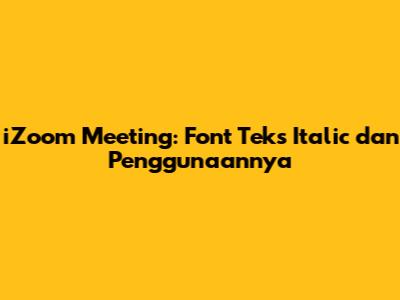
Hey guys! Pernah nggak sih kalian lagi asyik meeting online pakai iZoom, terus bingung sendiri pas lihat ada teks yang tampilannya miring alias italic? Nah, kali ini kita bakal kupas tuntas soal font italic di iZoom meeting. Apa sih sebenarnya fungsi teks italic itu, kenapa penting, dan bagaimana cara menggunakannya biar meeting kalian makin profesional dan informatif. iZoom, sebagai salah satu platform meeting online yang populer, terus berinovasi untuk memberikan pengalaman terbaik bagi penggunanya. Salah satu fitur kecil tapi penting yang seringkali terabaikan adalah kemampuan untuk memformat teks, termasuk menggunakan gaya italic. Tapi, banyak dari kita yang mungkin masih bertanya-tanya, kenapa sih ada teks miring? atau kapan sebaiknya saya pakai teks italic? Tenang, kalian datang ke tempat yang tepat. Kita akan bedah satu per satu, mulai dari definisi dasar sampai ke tips-tips praktis yang bisa langsung kalian terapkan. Jadi, siap-siap ya, karena setelah baca artikel ini, kalian bakal jadi pro dalam urusan formatting teks di iZoom meeting, bahkan mungkin di platform lain juga. Lupakan kebingungan soal teks italic, mari kita jelajahi dunia formatting yang seru ini bersama-sama! Memahami penggunaan teks italic yang tepat bisa jadi pembeda antara pesan yang sekadar tersampaikan dengan pesan yang benar-benar menonjol dan mudah dipahami. Ini bukan cuma soal estetika, lho, tapi lebih kepada kejelasan dan penekanan makna dalam komunikasi digital yang serba cepat ini. Yuk, kita mulai petualangan kita dalam memahami seluk-beluk italic di iZoom meeting.
Apa Itu Teks Italic dan Fungsinya?
Jadi gini, guys, teks italic itu apa sih? Sederhananya, italic adalah gaya penulisan di mana huruf-hurufnya terlihat sedikit miring ke kanan. Bayangin aja huruf biasa lagi santai, terus sedikit condong ke depan, gitu deh. Gaya ini biasanya digunakan untuk memberikan penekanan pada kata atau frasa tertentu dalam sebuah kalimat. Jadi, kalau kalian lihat ada kata yang dicetak miring, kemungkinan besar penulis ingin kalian memperhatikan kata itu secara khusus. Fungsinya banyak banget lho. Pertama, memberi penekanan. Ini fungsi utamanya. Misal, dalam percakapan iZoom, kamu mau menekankan satu poin penting, kamu bisa pakai italic. Contohnya, "Tolong selesaikan laporan ini sebelum jam 5 sore," nah, kata "Tolong" yang dicetak miring itu langsung menarik perhatian kan? Ini bikin audiens langsung tahu mana bagian yang paling krusial. Kedua, menunjukkan judul karya. Seperti judul buku, film, lagu, atau artikel. Jadi, kalau kalian lagi diskusi tentang sebuah karya, mencantumkan judulnya dalam format italic bakal bikin lebih rapi dan profesional. Misalnya, "Kita perlu mereferensikan artikel berjudul 'Strategi Pemasaran Digital Terbaru' untuk proyek kita." Ketiga, membedakan istilah asing atau kutipan. Kalau ada kata dari bahasa lain yang dipakai dalam bahasa Indonesia, atau kalau kalian mengutip langsung perkataan seseorang, italic bisa dipakai. Contohnya, kita sering dengar istilah "meeting point" dalam bahasa Inggris. Terus, kalau mengutip, bisa jadi seperti ini, "Seperti kata pepatah, 'Kesabaran adalah kunci.'" Keempat, menyoroti gagasan atau konsep baru. Kadang, dalam diskusi ilmiah atau teknis, ada istilah atau konsep yang baru diperkenalkan. Menggunakan italic bisa membantu membedakan ini dari teks biasa. Jadi, intinya, italic itu bukan sekadar gaya biar tulisan kelihatan keren, tapi punya peran penting dalam memperjelas makna, memberikan penekanan, dan meningkatkan keterbacaan. Di platform seperti iZoom meeting, di mana komunikasi seringkali cepat dan padat informasi, kemampuan menggunakan italic dengan tepat bisa jadi senjata ampuh buat bikin pesan kalian nggak cuma sampai, tapi juga dipahami dengan baik dan benar. Dengan memahami fungsi-fungsi ini, kalian bisa lebih percaya diri menggunakan italic untuk membuat komunikasi di iZoom meeting kalian jadi lebih efektif dan profesional, guys. Ini adalah elemen formatting dasar tapi sangat powerful.
iZoom Meeting dan Penggunaan Teks Italic
Nah, sekarang kita bahas gimana sih iZoom meeting itu sendiri terkait teks italic. Sejujurnya, kebanyakan platform meeting online, termasuk iZoom, biasanya nggak punya fitur dedicated untuk memformat teks secara real-time saat kalian lagi presentasi atau chat di dalam meeting itu sendiri, kecuali kalau kalian lagi pakai fitur whiteboard atau semacamnya yang memang mendukung editor teks. Tapi, jangan salah paham dulu, guys! Ini bukan berarti italic nggak relevan di iZoom meeting, lho. Justru sebaliknya, memahami dan menggunakan italic dengan bijak itu sangat penting, terutama kalau kalian menyiapkan materi presentasi atau catatan sebelum meeting dimulai. Misalnya, kalian lagi nyiapin slide presentasi pakai PowerPoint atau Google Slides, nah di situ kalian pasti punya opsi untuk bikin teks jadi italic. Ketika materi itu nanti kalian tampilkan di iZoom meeting, audiens akan melihat teks italic yang sudah kalian siapkan. Ini tujuannya agar informasi yang kalian sampaikan jadi lebih terstruktur dan mudah ditangkap. Penekanan pada poin penting akan terlihat jelas di slide, yang kemudian akan kalian jelaskan lebih lanjut secara lisan. Begitu juga kalau kalian bikin catatan untuk diri sendiri atau briefing untuk tim sebelum meeting iZoom dimulai. Menggunakan italic di dokumen catatan itu akan membantu kalian fokus pada poin-poin kunci saat sesi diskusi nanti. Jadi, meskipun iZoom meeting-nya sendiri mungkin nggak punya tombol 'Italic' yang bisa diklik langsung saat obrolan berlangsung, konsep dan penggunaan italic tetap krusial dalam persiapan dan penyampaian informasi. Pikirkan saja seperti ini: italic itu adalah alat bantu visual untuk menyampaikan nada atau makna tertentu dalam tulisan. Saat kalian membuat dokumen, e-mail, atau materi presentasi yang akan dibagikan atau dibahas di iZoom meeting, penggunaan italic ini membantu memecah kebosanan visual dan mengarahkan perhatian pembaca atau pendengar ke elemen-elemen yang paling penting. Contoh konkretnya, kalau kalian lagi bikin agenda meeting iZoom, kalian bisa bikin judul sesi pakai italic, atau kalau ada kata kunci penting yang perlu diingat, italicin aja! Ini membantu semua orang yang terlibat dalam meeting jadi lebih fokus dan nggak kehilangan track dari topik yang dibahas. Jadi, meskipun fitur built-in-nya mungkin terbatas saat meeting berlangsung, persiapan materi dengan format italic adalah kunci agar komunikasi di iZoom meeting jadi lebih efektif dan profesional. Ini tentang bagaimana kita menggunakan alat yang ada, bahkan di luar platform meeting itu sendiri, untuk menunjang kelancaran komunikasi kita di dalam platform tersebut. iZoom meeting kan cuma wadahnya, tapi konten dan cara penyampaiannya tetap ada di tangan kita, guys!
Kapan Sebaiknya Menggunakan Teks Italic di iZoom Meeting?
Oke, guys, sekarang kita masuk ke bagian yang paling seru: kapan sih momen yang tepat buat pakai teks italic pas lagi ngomongin atau nyiapin sesuatu buat iZoom meeting? Ini penting biar nggak salah kaprah dan malah bikin bingung. Ingat, italic itu bukan buat gaya-gayaan doang, tapi punya tujuan. Fungsi utama italic adalah penekanan, jadi pakai aja pas kalian mau bikin satu kata atau frasa jadi super penting dan harus diperhatikan sama semua orang di meeting. Misalnya, waktu kalian lagi ngasih arahan penting ke tim. Coba deh, bayangin kalian lagi ngomong di iZoom, terus ada poin yang kritis banget. Kalian bisa bilang, "Ingat ya, deadline pengumpulan data itu besok pagi, bukan lusa!" Kata "Ingat" atau seluruh frasa "Ingat ya, deadline pengumpulan data itu besok pagi, bukan lusa!" yang dicetak miring di catatan atau slide kalian, itu langsung bikin pendengar lebih fokus dan nggak salah paham soal tenggat waktu. Fungsi kedua yang nggak kalah penting adalah untuk identitas karya. Jadi, kalau kalian lagi diskusi tentang buku, film, lagu, atau bahkan nama proyek, nah itu pas banget kalau ditulis pakai italic. Contohnya di iZoom, kalian bisa bilang, "Kita perlu baca buku 'Atomic Habits' untuk dapat inspirasi." Ini bikin judul buku jadi jelas dan terpisah dari kalimat biasa. Kelihatan lebih profesional, kan? Terus, ketika kalian perlu menyoroti istilah asing atau istilah teknis yang mungkin belum familiar buat semua orang. Misalnya, ada istilah baru dalam dunia marketing yang lagi dibahas, kayak 'influencer marketing' atau 'SEO audit'. Menuliskannya dalam italic bisa membantu audiens membedakan ini sebagai istilah khusus. Ini juga berlaku kalau kalian pakai kutipan langsung dari sumber lain. Anggap aja kayak kalian ngasih tahu, "Ini bukan kata-kata saya, tapi kata-kata dari sumber lain." Contohnya, "Seperti yang disampaikan oleh Pak Budi, 'inovasi adalah kunci pertumbuhan bisnis.'" Ini menjaga integritas dan kejelasan sumber informasi. Terakhir, tapi nggak kalah penting, gunakan italic untuk membedakan peran atau status. Misalnya, kalau dalam satu dokumen ada daftar tugas, kalian bisa menandai tugas yang sifatnya urgent dengan italic. Atau, kalau kalian lagi diskusi soal peran dalam proyek, kalian bisa tulis: 'Project Manager', 'Lead Developer', 'Marketing Specialist' dalam format italic untuk menunjukkan peran-peran tersebut. Yang terpenting, jangan berlebihan, guys! Pakai italic secukupnya saja. Kalau terlalu banyak teks yang dimiringkan, efek penekanannya malah hilang dan bikin mata lelah. Gunakan secara strategis untuk poin-poin yang benar-benar butuh perhatian ekstra. Dengan memahami kapan dan bagaimana menggunakan italic dengan tepat, komunikasi kalian di iZoom meeting, baik itu saat persiapan materi, saat presentasi, maupun saat berbagi catatan, akan jadi jauh lebih efektif, jelas, dan profesional. Jadi, jangan ragu untuk memanfaatkan kekuatan italic ini, tapi ingat, kuncinya adalah moderasi dan tujuan yang jelas.
Tips Menggunakan Teks Italic Agar Lebih Efektif di iZoom Meeting
Supaya penggunaan teks italic kalian di iZoom meeting jadi makin nampol dan nggak sia-sia, nih ada beberapa tips jitu buat kalian, guys. Pertama, selalu utamakan kejelasan, bukan sekadar gaya. Ingat, tujuan utama italic adalah untuk memberi penekanan atau membedakan sesuatu. Jadi, sebelum kalian miringin teks, tanya dulu ke diri sendiri: 'Apakah ini benar-benar perlu?' Kalau jawabannya 'iya', baru deh pakai. Jangan sampai gara-gara italic, malah bikin orang bingung baca atau malah kelihatan norak. Penekanan yang cerdas itu kuncinya. Kedua, gunakan secara konsisten. Kalau kalian sudah memutuskan untuk menggunakan italic untuk menandai judul buku, misalnya, maka lakukan itu terus-menerus di semua materi yang berhubungan dengan iZoom meeting kalian. Konsistensi ini membantu membangun kebiasaan baik dan membuat audiens lebih mudah mengenali pola informasi. Jadi, mereka nggak perlu mikir dua kali, "Ini judul buku atau bukan ya?" Ketiga, padukan dengan elemen formatting lain dengan bijak. Italic memang bagus, tapi jangan sampai sendirian. Kalian bisa kombinasikan dengan bold untuk penekanan yang lebih kuat, atau pakai bullet points untuk daftar. Tapi ingat, jangan terlalu ramai. Terlalu banyak gaya formatting dalam satu kalimat atau paragraf itu bikin pusing. Cukup gunakan kombinasi yang membuat informasi lebih mudah dicerna. Kombinasi italic dan bold itu seringkali jadi pilihan yang bagus untuk menyoroti poin yang sangat penting. Keempat, perhatikan audiens kalian. Kalau kalian meeting dengan tim internal yang sudah paham jargon kalian, mungkin penggunaan italic untuk istilah teknis bisa lebih bebas. Tapi kalau audiensnya campuran, atau ada orang baru, lebih baik gunakan italic untuk istilah asing atau teknis dengan penjelasan tambahan. Tujuannya agar semua orang bisa on the same page. Memahami siapa yang membaca atau mendengar itu penting banget. Kelima, latih penggunaan italic dalam materi persiapan. Karena fitur italic di iZoom meeting saat sesi berlangsung mungkin terbatas, fokuslah pada bagaimana kalian bisa memaksimalkan penggunaannya di slide presentasi, dokumen, atau catatan yang akan kalian bagikan. Latih diri kalian untuk mengidentifikasi kapan sebuah kata atau frasa pantas untuk diberi penekanan italic. Keenam, hindari penggunaan italic untuk teks yang panjang. Italic itu efektif untuk kata atau frasa pendek. Kalau kalian miringin satu paragraf penuh, itu bakal susah dibaca dan bikin mata cepat lelah. Fokus pada detail, bukan keseluruhan. Terakhir, selalu review dan minta feedback. Setelah kalian menyiapkan materi dengan penggunaan italic, coba periksa kembali atau minta rekan kerja untuk melihatnya. Tanyakan apakah penekanan yang kalian buat sudah jelas atau malah membingungkan. Feedback ini sangat berharga untuk perbaikan ke depannya. Dengan menerapkan tips-tips ini, kalian nggak cuma bisa menggunakan teks italic dengan benar di iZoom meeting, tapi juga bisa meningkatkan kualitas komunikasi dan profesionalisme kalian secara keseluruhan. Jadi, yuk, mulai praktekkan sekarang, guys!
Kesimpulan: Italic di iZoom Meeting, Pakai Kapan dan Kenapa?
Jadi, guys, setelah kita ngobrol panjang lebar soal font italic di iZoom meeting, kesimpulannya apa nih? Intinya, italic itu lebih dari sekadar gaya miring pada huruf. Italic adalah alat komunikasi visual yang ampuh untuk memberikan penekanan, menyoroti judul karya, membedakan istilah asing atau kutipan, dan memperjelas informasi penting. Meskipun iZoom meeting sendiri mungkin nggak selalu menyediakan fitur format langsung saat obrolan berlangsung, penggunaan italic dalam materi persiapan seperti slide presentasi, dokumen, atau catatan itu sangat krusial. Kenapa? Karena ini membantu meningkatkan kejelasan, fokus, dan profesionalisme komunikasi kalian. Kapan harus pakai? Gunakan saat ada kata atau frasa yang ingin kalian tekankan agar audiens nggak melewatkannya, saat menulis judul buku/film/lagu, saat menggunakan istilah asing atau kutipan, dan untuk membedakan elemen penting lainnya. Tapi ingat, kuncinya adalah moderasi dan tujuan yang jelas. Jangan sampai italic malah bikin tulisan jadi susah dibaca atau terlihat berlebihan. Gunakan secara strategis hanya pada poin-poin yang benar-benar butuh perhatian ekstra. Dengan memahami fungsi dan cara penggunaan italic yang tepat, kalian bisa membuat diskusi atau presentasi di iZoom meeting jadi lebih efektif, informatif, dan berkesan. Jadi, lain kali saat kalian menyiapkan materi untuk iZoom meeting, jangan ragu untuk memanfaatkan kekuatan italic ini. Ingat, sedikit sentuhan italic yang tepat bisa membuat perbedaan besar dalam cara pesan kalian diterima. Keep communicating effectively, guys!